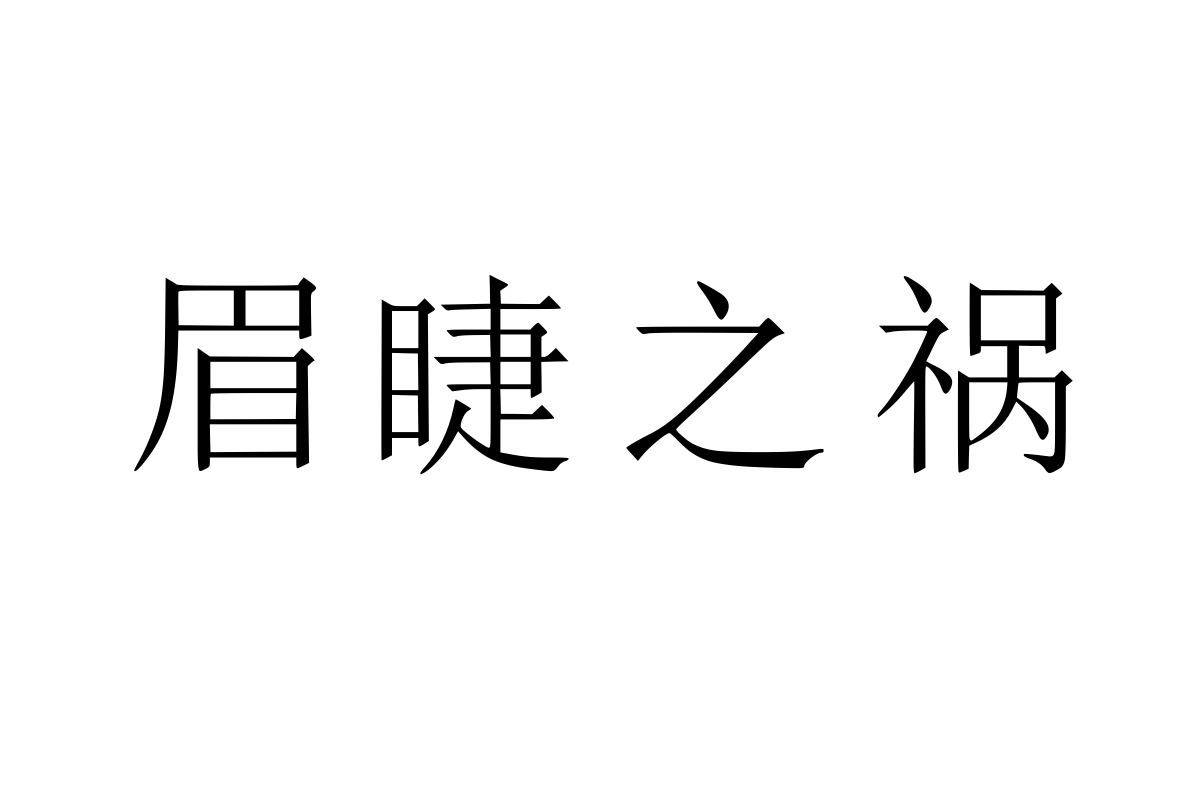
兰米宋体是一种中文字体,属于宋体字系列。它由北京兰米科技有限公司开发,具有现代感和艺术气息的特点。兰米宋体采用独特的笔画结构,使得字形更加流畅和美观。它的设计灵感来源于传统的书法艺术,但又融入了现代元素,使得字体既有传统韵味又不失现代感。
兰米宋体适用于各种场合,包括广告、海报、书籍、杂志等。它的可读性非常好,适合用于需要清晰阅读的场合。同时,兰米宋体也适用于需要展示艺术气息的场合,如文艺作品、展览等。
总的来说,兰米宋体是一款非常优秀的中文字体,具有很高的艺术价值和实用价值。